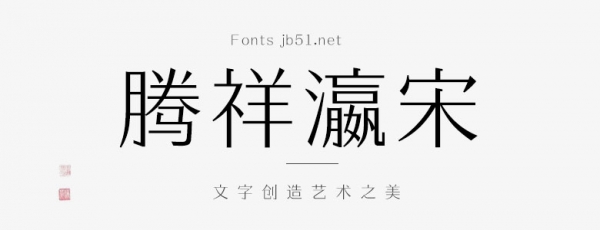
騰祥瀛宋簡(jiǎn)W1是一款不錯(cuò)的藝術(shù)字體,由騰祥字庫(kù)出品,這款字體筆觸纖細(xì),字形端正,具有很好的視覺(jué)感,適合應(yīng)用于藝術(shù)設(shè)計(jì)、平面宣傳設(shè)計(jì)、網(wǎng)頁(yè)設(shè)計(jì),書(shū)法字帖等領(lǐng)域,需要的朋友可以前來(lái)本站下載。